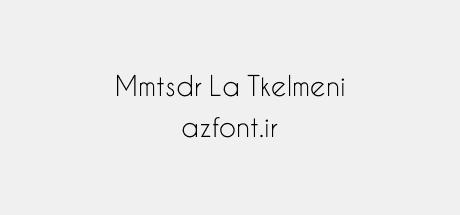
فونت زیبای رایگان Mmtsdr La Tkelmeni
قلم زیبای Mmtsdr La Tkelmeni از سری قلم های بسیار زیبا برای تایپوگرافی و لوگو تایپ می باشد.این قلم در وزن Regular و توسط ar.photoshop.3abber.com طراحی و منتشر شده است.